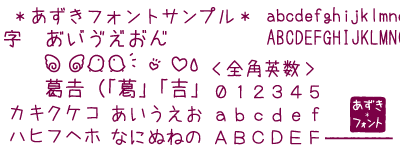
Berikut ini kumpulan font aksara Jepang (Kanji, Hiragana, dan Katakana) dengan berbagai macam bentuk (tulisan tangan, kuas, dan lain-lain).
Google Fonts memiliki 31 font Jepang. Baik yang berbentuk tulisan tangan (Handwriting); maupun yang berbentuk Display, Serif, Sans Serif, dan Monospace. - 36 Cool Katakana Design Fonts Free Download